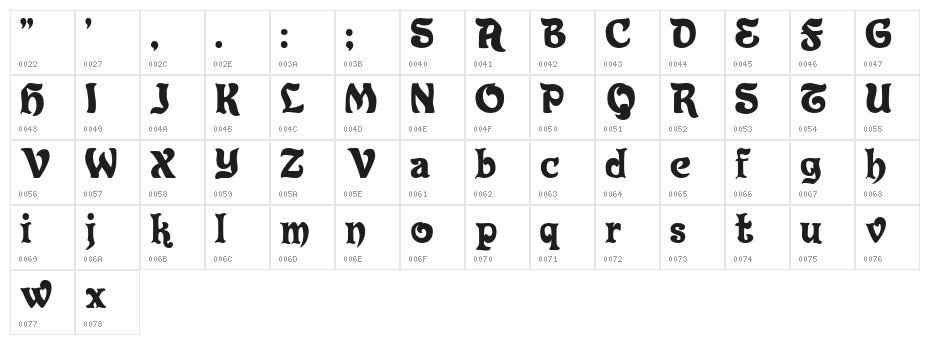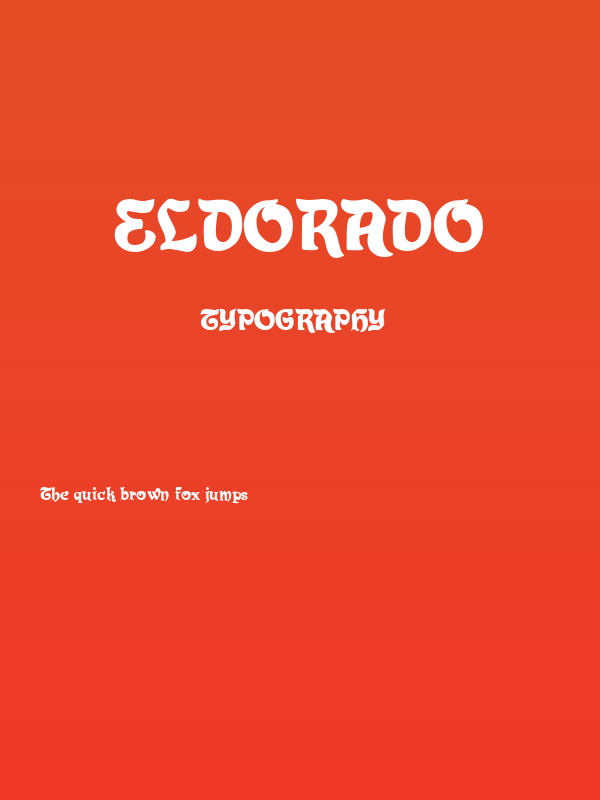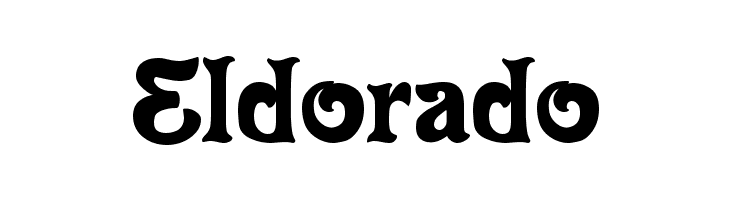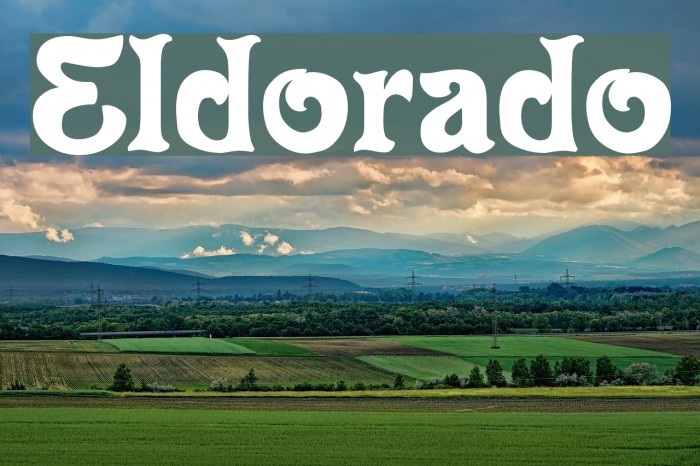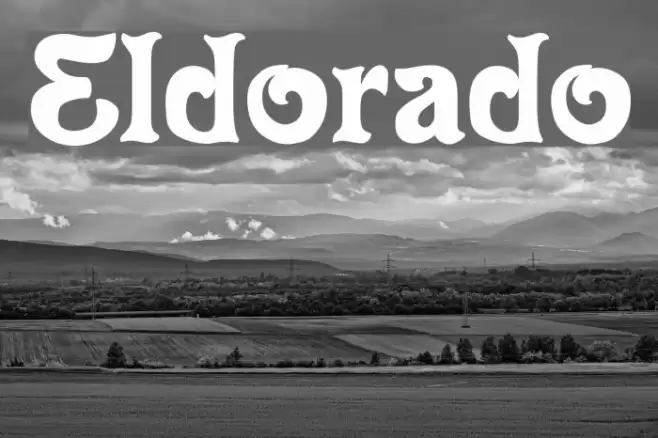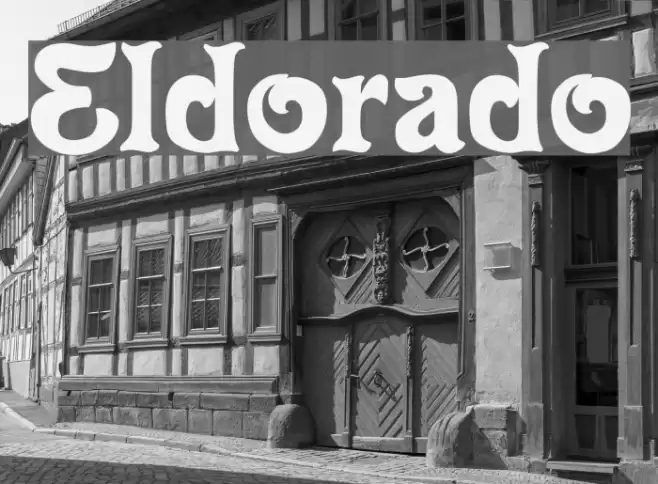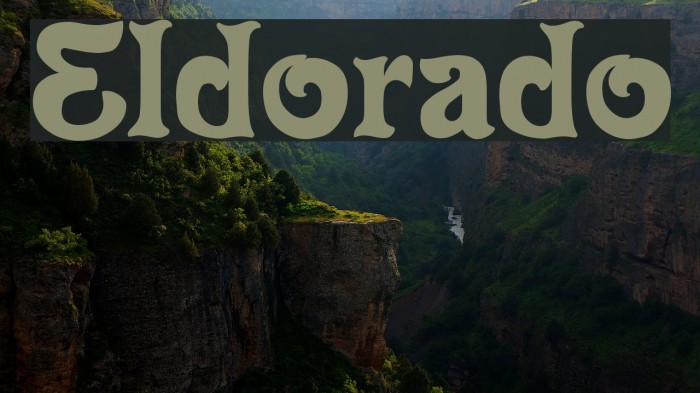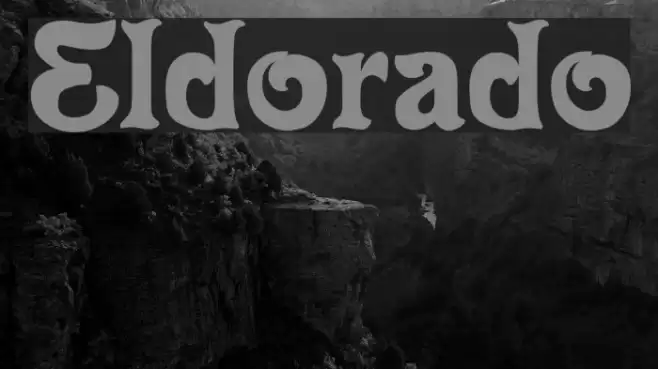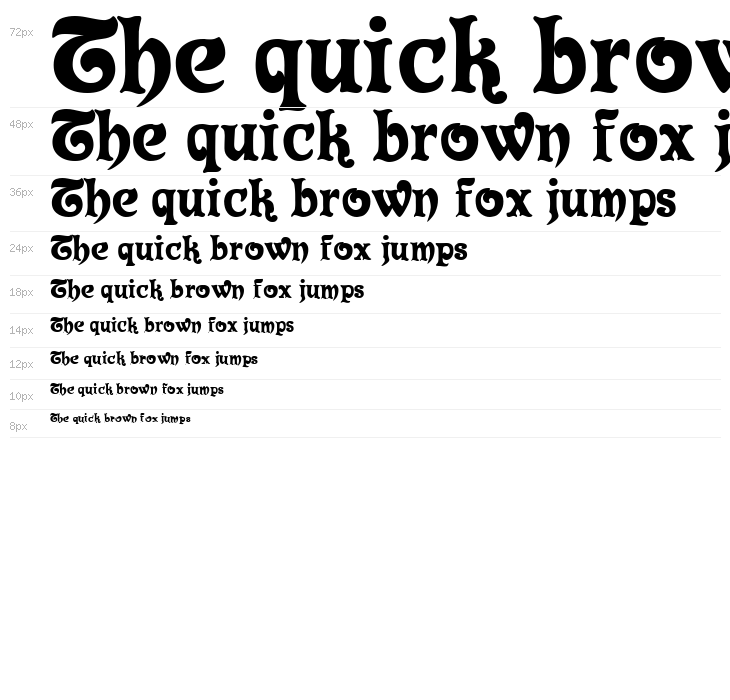
Eldorado Font
| Vorgeschlagene Projekte | Ideal for fantasy-themed designs, book covers, posters, and branding that requires a historical or dramatic touch. |